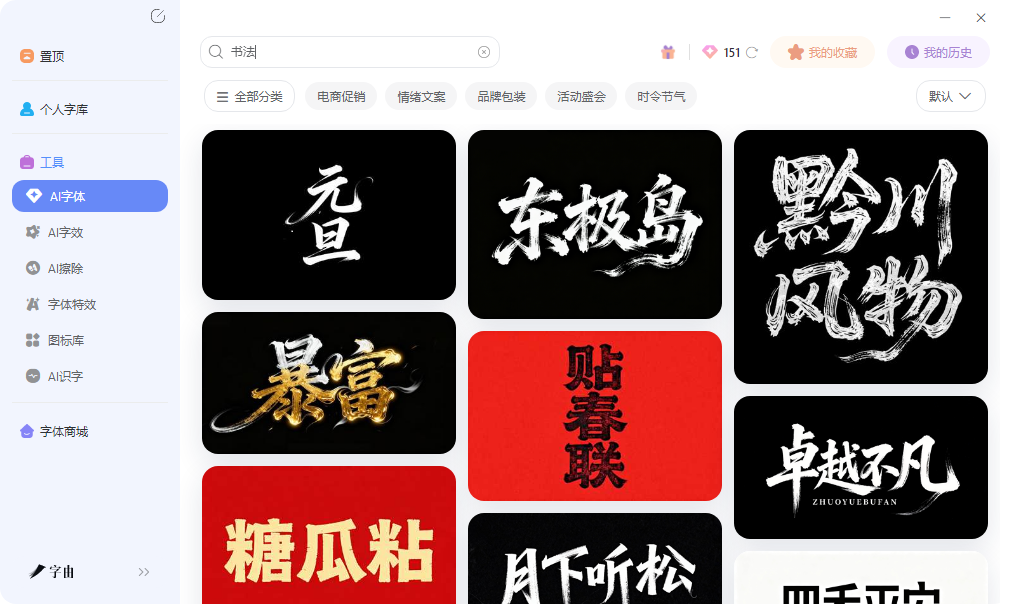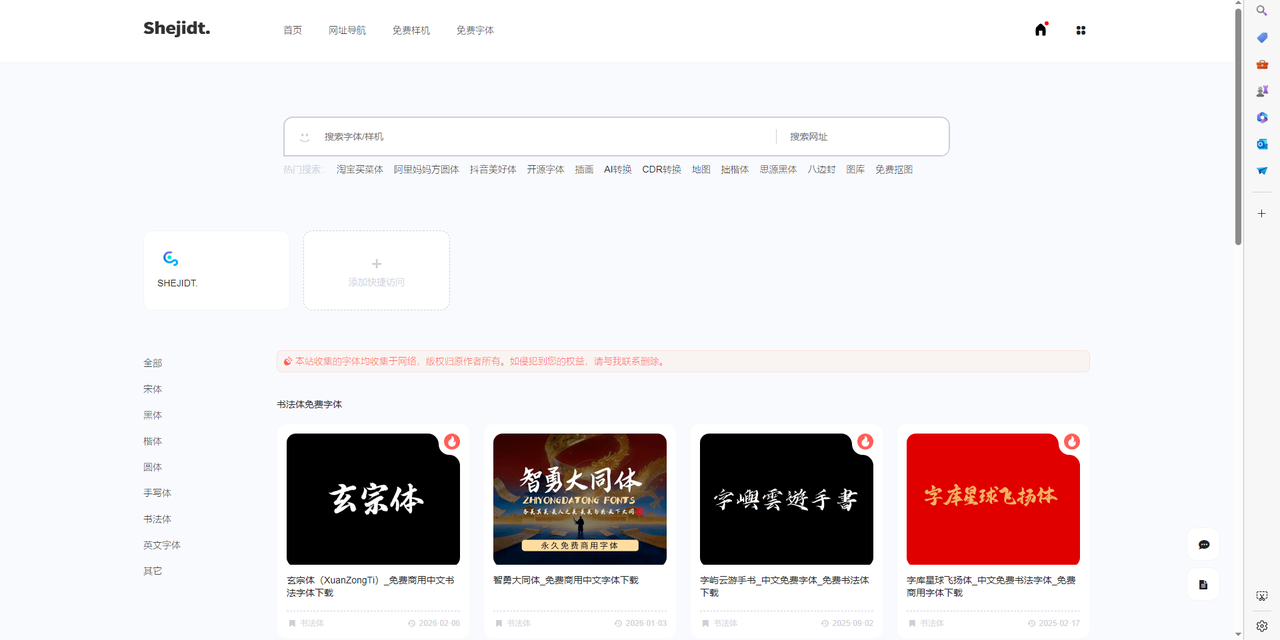
免费商用书法字体推荐,行书楷书隶书直接找齐
做中式风格的设计,书法体往往是点睛之笔。海报上的大标题用行书显得洒脱,品牌标语用楷书显得稳重,文创包装用隶书显得古朴。但找一款能商用的中文书法体并不容易,很多看起来不错的字体实际上只限个人使用。这篇文章整理了五个平台,专门解决免费商用书法字体的下载问题。
字由的字体库中,书法体是单独的一个分类,和手写体区分开来。书法体偏向传统书体的数字化再现,行书、楷书、隶书、草书等类型都有覆盖;手写体则更偏向现代人日常书写的笔迹感。这种区分在做不同气质项目时比较实用。
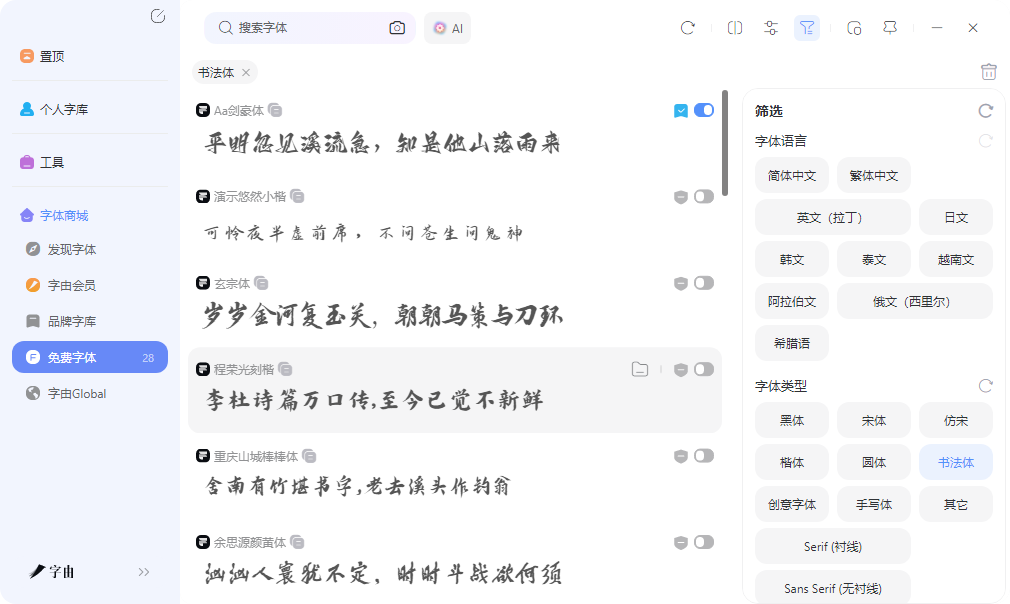
AI字体功能对书法体需求也有帮助。模板库里有不少书法风格的特效模板,水墨渲染、鎏金质感、毛笔飞白等方向都有。如果项目中需要的不是字体文件本身,而是一张带书法效果的艺术字图片,AI字体可以直接生成透明背景的PNG,拖进设计稿就能用。这种方式比找书法体再自己调效果要快不少。
Shejidt是一个设计导航站,除了字体外还收录了样机、图标、工具等资源。它的字体板块里有一个书法体免费字体分类,专门整理了可以免费下载的书法体资源。
分类里展示了玄宗体、智勇大同体、字屿云游手书、字库星球飞扬体等多款书法字体。左侧导航还提供了宋体、黑体、楷体、圆体、手写体等基础书体分类,方便在不同书体之间切换浏览。顶部的搜索框支持输入关键词查找特定字体。
这个站的优势在于把散落在各处的免费商用书法字体资源集中到了一个页面,省去了逐个网站翻找的麻烦。每款字体都有预览图和标题说明,点击可以进入详情页获取。对于想要快速浏览一批书法体、找到合适资源的设计师来说,这里的整理比较直观。
站长字体是国内比较老牌的字体下载站,中文字体板块下有专门的书法字体分类。页面上的筛选维度比较多,品牌维度包括免费商用、汉仪、方正、字魂等;风格维度包括隶书、行书、手写、书法、毛笔、草书等,可以交叉筛选快速定位。
展示的书法字体风格跨度较大,方正楷体偏向传统楷书规范,点字隽永带有钢笔书法的精致感,山海格桑卓玛则是藏式书法风格,山海盛唐榜书有榜书的大气。这种多样化的选品让站长字体作为免费商用书法字体的来源,能够覆盖不同气质的中式设计需求。
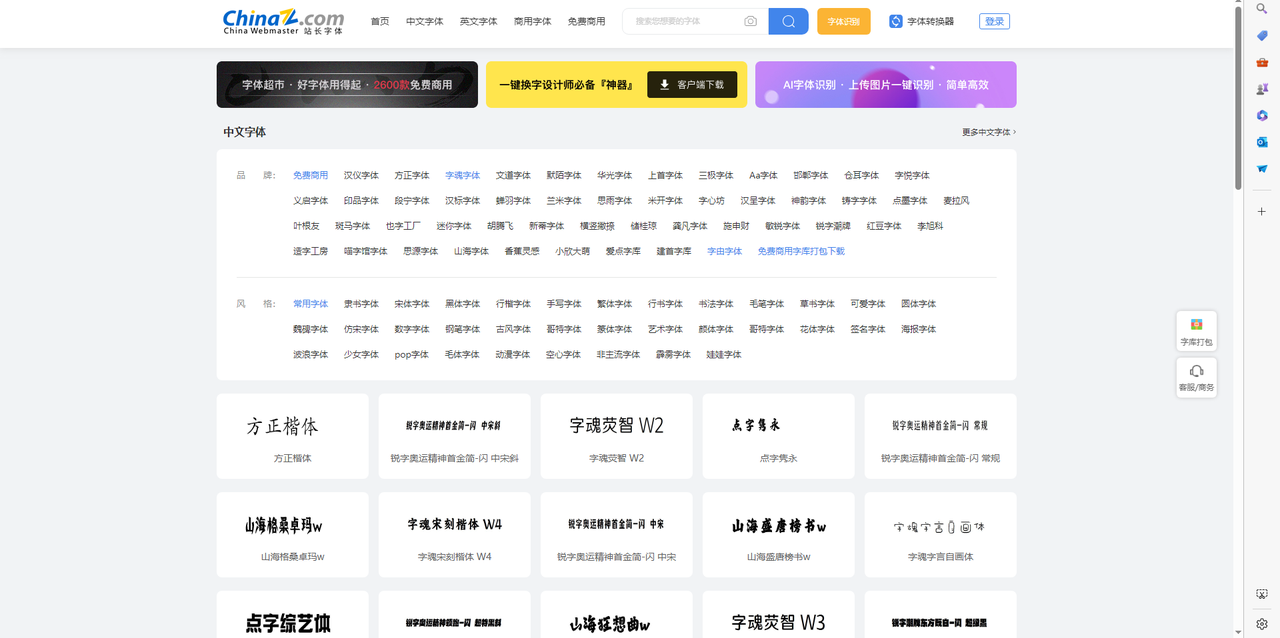
模板王的字体下载板块中,书法体是一个独立分类,目前收录了250款书法字体资源。左侧导航按书体做了细分,宋体425款、楷体304款、行书191款、隶书172款、草书24款、行楷148款等,每个分类都标注了具体数量。
书法体分类里展示了也字工厂花笺小楷、春梅手书、浮生行楷、王强书法体、巴蜀墨迹、庞门正道粗书体、刻石录颜体、游龙行楷等多款资源。风格从娟秀小楷到豪放行楷都有,适合不同场景的中式设计项目。部分字体标注了商免标签,说明允许商业使用。
模板王的细分书体分类在同类平台中做得比较细,想做行楷就点行楷分类,想用小楷就点小楷相关资源,不需要在大量无关结果里翻找。对于需要免费商用书法字体、且有明确书体方向的设计师来说,这里的导航效率比较高。
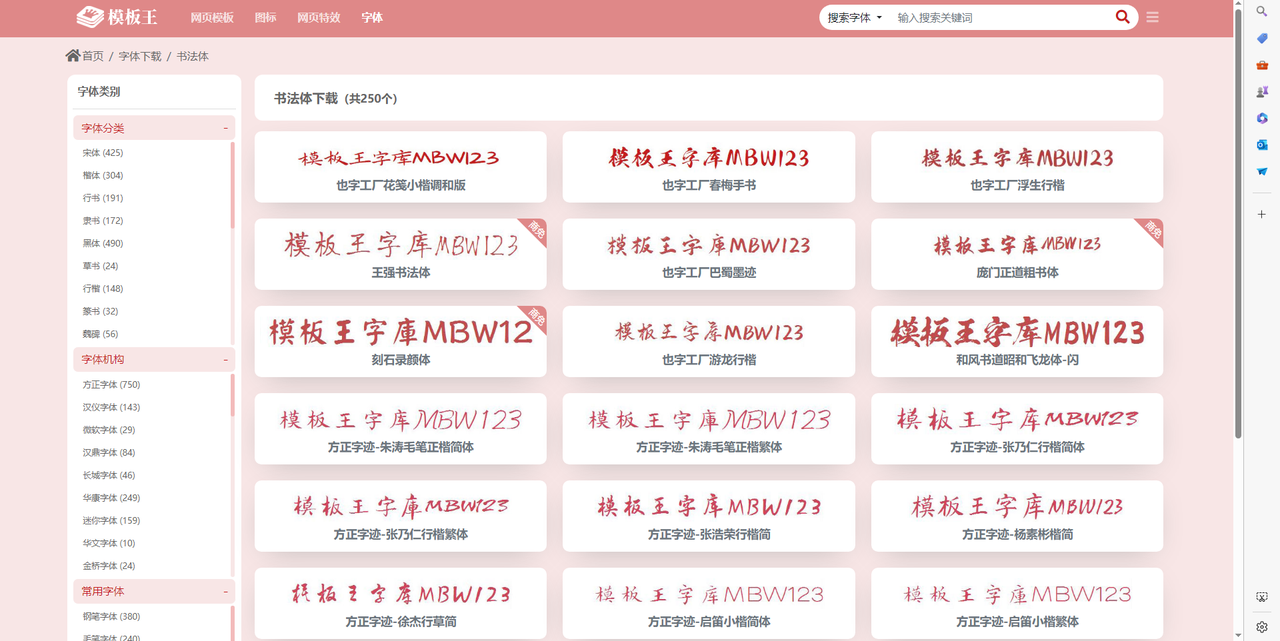
字体类型筛选里包括书法、行书、手写等分类,字体风格里还有中国风、手写风等标签。精品推荐区域展示了PF频凡胡涂体、写意体、Unifont点阵黑、三极力量体等热门资源,每款都标注了浏览量和下载量,受欢迎程度一目了然。